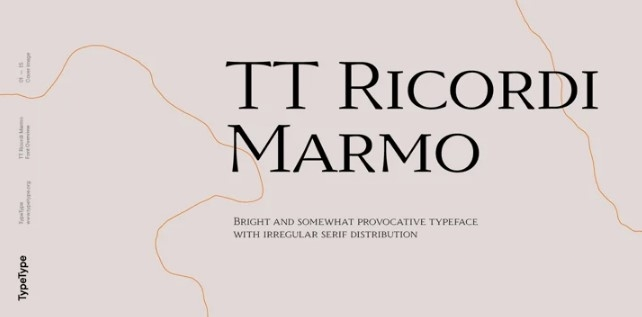
Название: TT Ricordi Marmo Font (2021)
TT Ricordi Marmo продолжает серию экспериментальных проектов в рамках коллекции шрифтов TT Ricordi. Основная цель проекта TT Ricordi - поиск драгоценных камней в старых надписях и на камне и возвращение этих надписей к жизни в виде современных шрифтов с зонтичным названием TT Ricordi.
TT Ricordi Marmo - оригинальный экспериментальный проект Евгения Танцурина, вдохновленный надписями в базилике Санта-Кроче во Флоренции. Работая над ним, мы хотели создать современный шрифт, который объединил бы элементы флорентийского sans-serif в сочетании с более традиционными визуальными решениями, характерными для засечек того периода. В результате мы получили яркий и несколько провокационный шрифт с неравномерным распределением засечек, необычными очертаниями и свободным духом.
При небольшом размере корпуса TT Ricordi Marmo производит нейтральное впечатление, но по мере увеличения размера пользователь отправляется в игривый поиск интересных ходов, графических особенностей и необычных решений. TT Ricordi Marmo отлично подходит для оформления плакатов, упаковки, нанесения крупных и средних надписей. Благодаря своей идиосинкразии, шрифт может хорошо смотреться как на афише в большом академическом театре, так и на кислотной рейв-вечеринке.
Вы можете найти набор шаблонов иконок, которые можно использовать несколькими способами. Во-первых, вы можете заменить буквы этими узорами, получив таким образом надпись с видимым графическим элементом. Затем вы также можете построить границы и интервальные метки или просто использовать их как значки. Все узоры идеально адаптированы к дизайну букв шрифта.
TT Ricordi Marmo состоит из 2 стилей и одного изменяемого шрифта. Каждый из стилей содержит более 630 глифов и 18 функций OpenType. Поскольку мы с самого начала задумывали TT Ricordi Marmo как плакатный шрифт, в нем вместо строчных букв используются маленькие прописные. Кроме того, шрифт имеет набор интересных лигатур, стилистических чередований, указателей, стрелок и пиктограмм.
Название: TT Ricordi Marmo Font (2021)
TT Ricordi Marmo продолжает серию экспериментальных проектов в рамках коллекции шрифтов TT Ricordi. Основная цель проекта TT Ricordi - поиск драгоценных камней в старых надписях и на камне и возвращение этих надписей к жизни в виде современных шрифтов с зонтичным названием TT Ricordi.
TT Ricordi Marmo - оригинальный экспериментальный проект Евгения Танцурина, вдохновленный надписями в базилике Санта-Кроче во Флоренции. Работая над ним, мы хотели создать современный шрифт, который объединил бы элементы флорентийского sans-serif в сочетании с более традиционными визуальными решениями, характерными для засечек того периода. В результате мы получили яркий и несколько провокационный шрифт с неравномерным распределением засечек, необычными очертаниями и свободным духом.
При небольшом размере корпуса TT Ricordi Marmo производит нейтральное впечатление, но по мере увеличения размера пользователь отправляется в игривый поиск интересных ходов, графических особенностей и необычных решений. TT Ricordi Marmo отлично подходит для оформления плакатов, упаковки, нанесения крупных и средних надписей. Благодаря своей идиосинкразии, шрифт может хорошо смотреться как на афише в большом академическом театре, так и на кислотной рейв-вечеринке.
Вы можете найти набор шаблонов иконок, которые можно использовать несколькими способами. Во-первых, вы можете заменить буквы этими узорами, получив таким образом надпись с видимым графическим элементом. Затем вы также можете построить границы и интервальные метки или просто использовать их как значки. Все узоры идеально адаптированы к дизайну букв шрифта.
TT Ricordi Marmo состоит из 2 стилей и одного изменяемого шрифта. Каждый из стилей содержит более 630 глифов и 18 функций OpenType. Поскольку мы с самого начала задумывали TT Ricordi Marmo как плакатный шрифт, в нем вместо строчных букв используются маленькие прописные. Кроме того, шрифт имеет набор интересных лигатур, стилистических чередований, указателей, стрелок и пиктограмм.